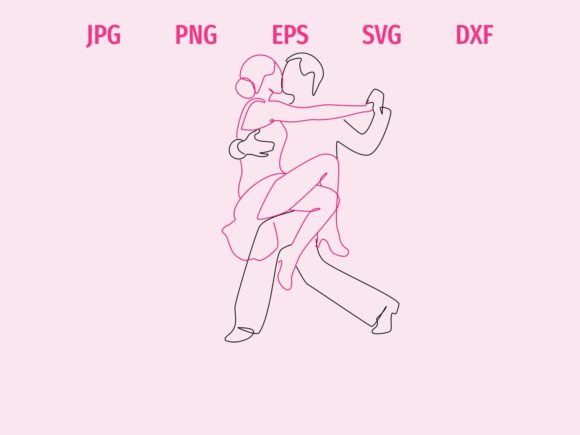
Love on the Dance Floor
適切なデザイン要素を見つけるのは難しい場合がありますが、Love on the Dance Floorは作品を即座に引き立てる優れたコレクションを提供します。
POD(オンデマンド印刷)製品、結婚式の招待状、またはソーシャルメディアのグラフィックを作成している場合でも、Love on the Dance Floorは理想的です。